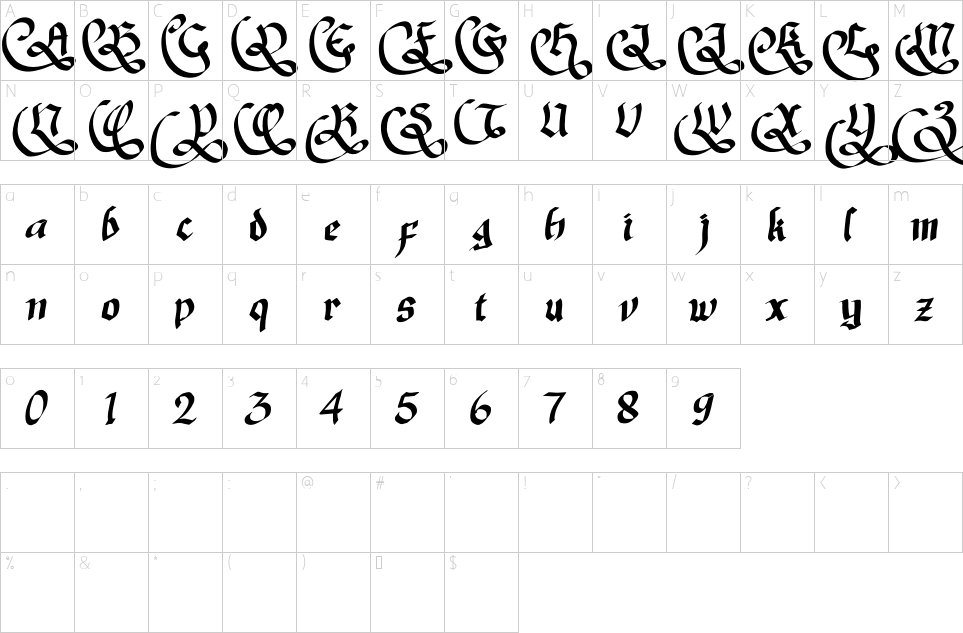
Descubra Antikan Rayo, uma elegante e sofisticada fonte para sua próxima criação gráfica. Desenhada pelo designer Yoga Letter, Antikan Rayo oferece uma combinação perfeita de rusticidade e modernidade, adaptável a uma variedade de projetos, desde sites pessoais até materiais de marketing digital. Com seu design cuidadosamente refinado, Antikan Rayo torna-se o complemento perfeito para qualquer projeto. Recentemente baixada por 1.397 usuários, essa fonte é uma escolha inteligente para aqueles que buscam qualidade e versatilidade em seu projeto. Não deixe de explorar Antikan Rayo para adicionar um toque único e autêntico a seus projetos. Descubra mais hoje mesmo!